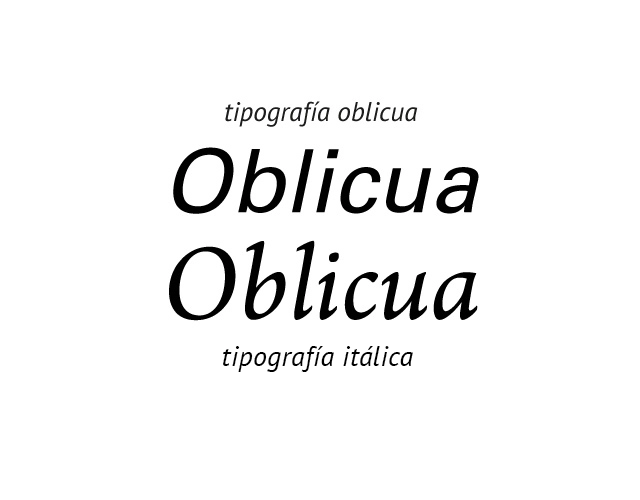
Es una variable tipográfica cuyos signos se presentan inclinados hacia la derecha. La itálica, deriva de las formas de la escritura conocida históricamente como cancilleresca.
En diseño editorial, frecuentemente se utilizan para resaltar palabras que se encuentran en otro idioma dentro del texto, títulos de obras o para uso metalingüístico.
La itálica o bastardilla se diferencia de la oblicua porque algunos signos tiene una estructura diferenciada, mientras que la oblicuas son la misma estructura que las rectas o roman pero inclinadas, evidente en la «a », la « g».
Frecuentemente se la llama erróneamente cursiva, pero ésta tiene otra estructura que responde a la fluidez de la escritura.